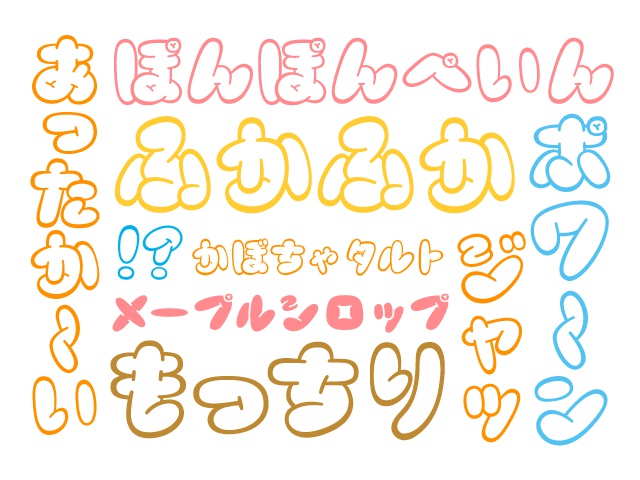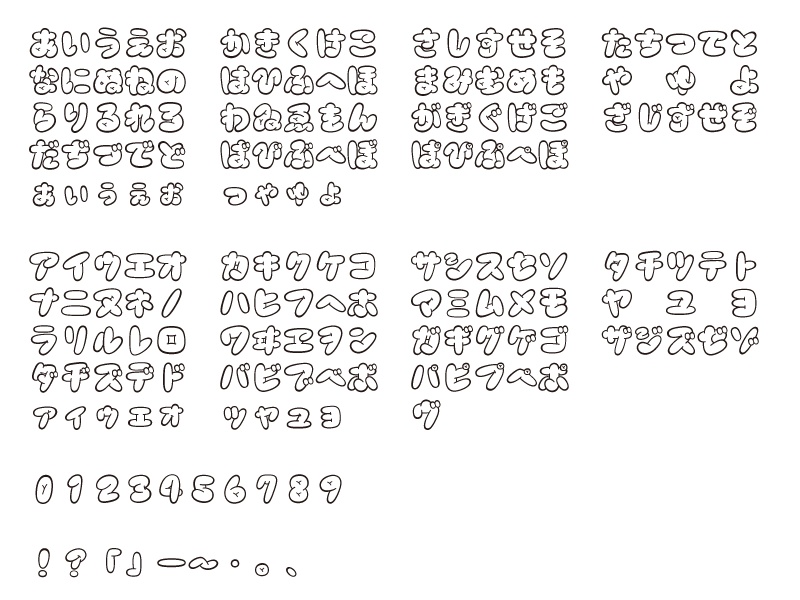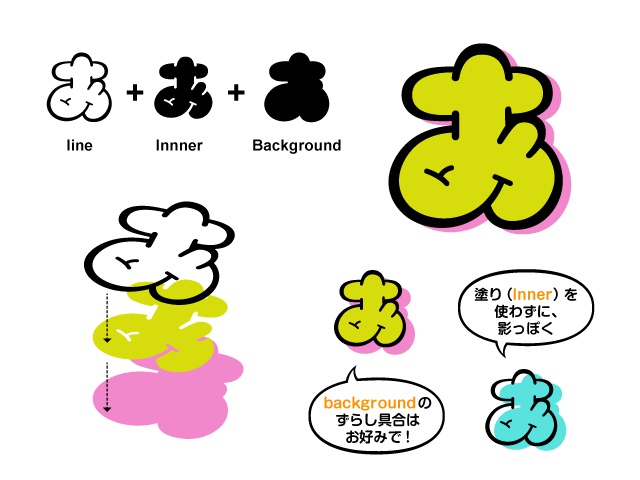
ぱんきじ かな フォント(商用利用版)
ふんわり、もっちり感のあるかな文字書体です。 タイトル字などでインパクトが欲しい場合にぜひ! オノマトペとの相性も良いですよ。 【有料版のみ】 各ウェイト(Line,Inner,Background)を組み合わせることで レイヤードフォントとして使えます。 こちらは商用利用をお考えの方向けの有料版です。 (無料版はこちらから。お試しの場合もこちらからどうぞ! https://nomuraya.booth.pm/items/706099) 以下の利用規約を必ず読んでからお使いください。 【ぱんきじ かな】 ・opentypeフォント ・縦書き対応 できること OK ○印刷物、WEB、映像作品等で使用すること ○ロゴマークとして使用すること ○当フォントを加工、変形して使用すること ○当フォントを利用してのノベルティグッズなどの制作 ※利用報告不要・クレジット表記不要 ご遠慮ください NG ×当フォントそのものを再配布したり販売すること ×当フォントファイルを加工し、再配布したり販売すること ×当フォントを使ったロゴマークの商標登録 ×誹謗中傷の目的での使用 ※著作権は放棄しておりません。 ※利用条件は予告なく変更することがあります。 ※当フォントをダウンロード・インストール・使用した際に発生したあらゆる問題において当方の責任を負わないものとします。 ※スマートフォン、タブレットでのダウンロードについては動作確認等は行っておりません。